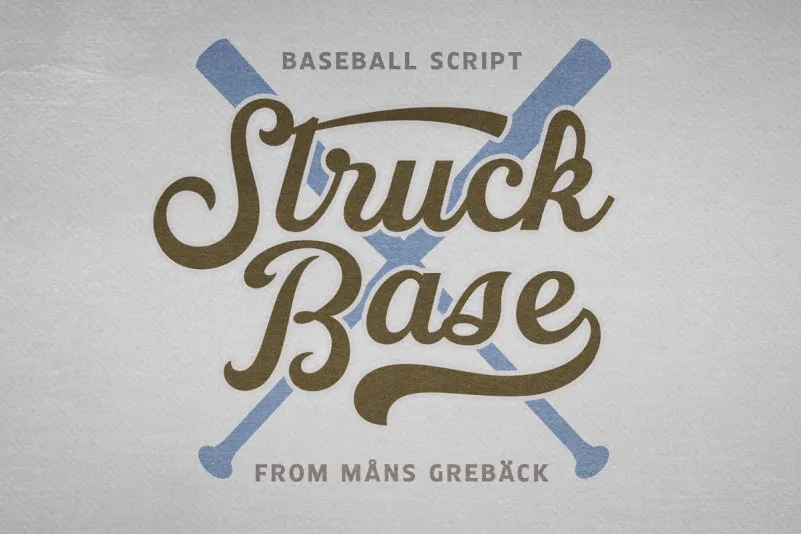
Esta é uma fonte script delicada e curvilínea criada pelo designer Mans Greback em 2021. Com um estilo esportivo e uma personalidade forte, ela pode se adaptar a ambientes tanto suaves quanto agressivos, abrangendo estilos tanto modernos como tradicionais. Suas cores vibrantes permitem que seja usada de maneira elegante para criações de moda jovem ou com um toque mais formal para cartões de aniversário. Seja na tatuagem, ou durante a celebração de um grande evento especial como casamento, Struck Base Font é uma escolha versátil e única. Combinar suas linhas suaves com um estilo robusto, ela se presta bem tanto para as nuances femininas quanto para os traços masculinos, tornando-se uma opção ideal para criações gráficas de alta qualidade no Brasil.